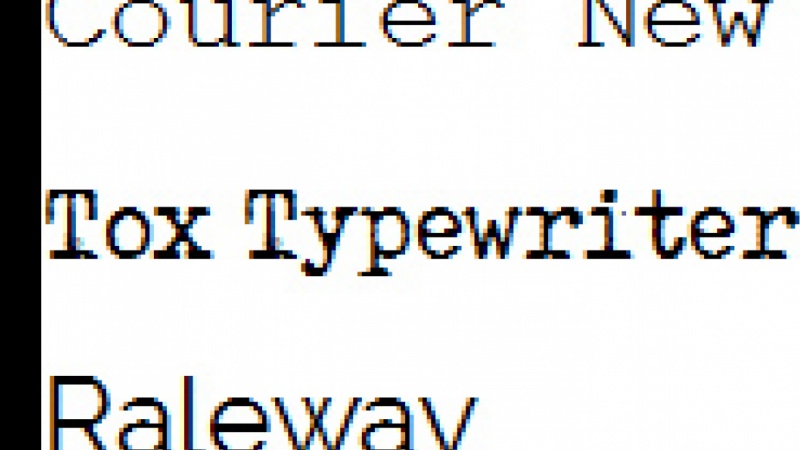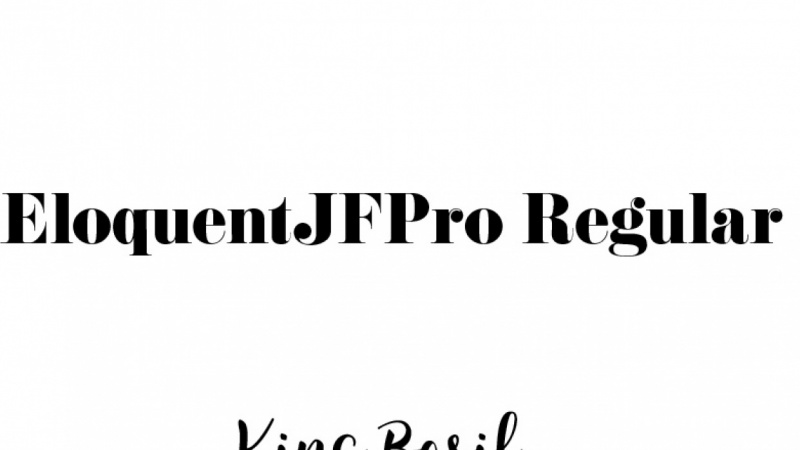
1. Fundamentos de tipografía cómo elegir las mejores fuentes: si alguna vez deambulaste cómo usar la tipografía para que tus proyectos luzcan profesionales donde
querías cómo elegir los mejores fondos? ¿ Encontrarás una gran fuente de respuestas, pues en esta clase aprenderás todos los fundamentos de tipografía necesarios que te harán ir con cualquier tipo de proyecto de diseño que use tipo. Gracias a esta clase, podrás elegir los mejores fondos para tu proyecto, identificar el fondo del que te enamoraste a primera vista y encontrar un montón de buenos fondos tú mismo y decir si vale la pena conseguir. Es una tienda de una sola parada para todos ustedes principiantes que quieran aprender fundamentos de tipografía de una concisa y directa al punto camino adentro, encontrarán respuestas a preguntas como ¿Qué es bueno? topografía fue la diferencia entre una tipografía
2. 1Cómo elegir las mejores fuentes: bienvenido a tomar los fundamentos de Pa Griffey. Cómo Elegir los fondos pasados Ninguna tipografía está contigo dondequiera que vayas al trabajo en la escuela, casa en una tienda por todas partes. Imagínate leyendo un artículo en tu periódico favorito navegando por la Web para conocer lo que es bueno del mundo. O tal vez estás revisando la tarea o el diseño de alguien. Cuál currículum es mejor. Ahí hay tarjetas de visita. Línea en su escritorio, correo de bancos y oficinas o manual para una impresora nueva. Café para ir de su cafetería favorita y estás mirando un cartel colgado en tu pared que dice, Haz más apagado por lo que te hace feliz. Solo quieres echar un vistazo fuera de tu ventana, y no puedes perderte una enorme cartelera invitándote al cine para ver la última película de Woody Allen. Incluso si no eres un escritor profesional o el mismo pensamiento de escribir algo te hace sentir que estás a punto de ser presentado a toda la Inquisición, definitivamente
has escrito algo en el pasado, o al menos reescrito. Podría haber sido un ensayo científico. Reanudar una carta a un cliente o un informe financiero anual. Podrías ser blogger o has diseñado tus propias invitaciones de boda o etiquetas para tarros con especias. O tal vez estás a punto de empezar a diseñar sitios web, logotipos o diversos materiales impresos. Cada vez que pones algún impuesto en el proyecto en un papel o en una pantalla de computadora, haces que la tipografía suceda, hablando
brevemente a tu tipógrafo y este curso trata de que te conviertes en
tipógrafo de bateador .
3. 2Qué es la tipografía: Entonces, empecemos con las tres cosas importantes que debes saber sobre la tipografía. Entonces, en realidad, ¿qué es la tipografía? Si bien la tipografía está diseñando letras, números y signos, es letras, números, signos, palabras, oraciones, párrafos, columnas y blanco espacios de alguna manera, por lo que crean una integridad armoniosa, limpia y atractiva, que está sirviendo al texto y al lector Recuerda respetar a tu lector. La tipografía debe estar sirviendo al lector, no a la oferta. Una famosa Strider ha estado realmente comprometida con escribir su nuevo libro. Un blogger está poniendo otro interés en post sobre su blogueado. Un diseñador está inmerso en crear un nuevo póster. Todos los creadores dedican mucho tiempo a los proyectos para hacerlos tan perfectos como
sólo pueden ser. Pero los lectores no tienen tanto tiempo. Los lectores buscan información. Quieren aprender algo,
revisar algo, obtener una opinión para que naveguen por miles de sitios web y libros. Leerán en Lee aquellos que demostraron valer la pena su tiempo. No leerán un artículo ilegible. No volverán a una página web donde no puedan encontrar nada. Tampoco volverán a un blawg caótico. Es más importante cómo escribes algo, no lo que escribes, al
menos al principio,
Y la tipografía es una herramienta que te ayuda a captar la atención del lector. Una buena topografía hará que el lector note el contenido que es significativo para el otro. Mucho más rápido. No tendrás que perder tiempo para leer todo el texto para decidir qué es importante o qué intentó decir el autor. Aunque el impuesto sea excepcional, Pero fue escrito usando calibri de 10 puntos, el lector se aburrirá con él. Nunca volveré a ello. Una buena topografía ayudará a fortalecer el texto, significado y mantener la atención del lector por más tiempo. A veces extrañamente es mejor que bonito. La tipografía debe ser útil. topografía es una forma fuera del arte aplicado. No tiene sentido diseñar letreros viales usando un fondo funky porque perderán su
propósito principal . En lugar de ser informativos, se
volverán distrayentes. El objetivo de una buena tipografía es aumentar el significado de la información que queremos
transmitir al lector. No importa cuánto lo intentemos, cuánto tiempo los pasemos eligiendo los fondos o configurando el koerting, todo
será para nada si el lector no puede leer mensaje
4. 3Whats la diferencia entre un tipo y una fuente: ¿ Cuál es la diferencia entre un tipo de letra y un fondo? Creo que el mayor error que comete la gente al hablar de tipografía es tratar tipografías y las fuentes como sinónimos. Recuerda, este tipo se enfrenta a una recaudación de fondos relacionados. Se puede pensar en una tipografía como un diseño de una familia de tipos y como cada tipo de familia, las familias tienen nombres y un ejemplo de un nombre de familia tipo es Laura. tipografías son diseños como Laura Monserrat o Poppins, y los diseñadores de tipos crean tipos de letra. Laura es una familia de tipografías. Una tipografía, no un fondo de fondo, es tipo en una tipografía, un miembro de una tipografía, familia o una variante de una tipografía. Entonces volvamos a nuestra tipografía Laura. Ejemplo. Laura Regular, Laura Italic, Laura Bold y Laura Bolt Italics son todos fondos de la tipografía Laura. Un fondo es en realidad cualquier variante en una tipografías espera con estilos y tamaño. Por ejemplo, cursiva de
32 puntos de flora es un fondo, y también lo es 24 Laura Bold. A veces la gente piensa que las fuentes son realmente tipografías digitales, mientras que las tipografías son físicas. El convenio de nomenclatura es el mismo para el tipo digital y físico. Rostros fondos referidos toe esperas con estilos y tamaños y tipografías son algo así como nombres
colectivos off sets off fondos relacionados. En ocasiones, a una tipografía se le conoce como familia de fuentes. Si te gusta un diseño Web, probablemente
te hayas encontrado con familias formadas en lugar de tipos de letra.
5. 4¿Qué es las Typefaces más importantes: hay miles de tipos de letra y fondos diferentes. Es por ello que es difícil llegar a una clasificación que satisfaga a todos . Existen muchas formas diferentes de clasificar tipos de letra, dependiendo del tiempo que se hicieron. Proporciones de estilo técnico, estado de ánimo que crean y demás. Por lo que para los efectos de este curso, vamos a enfocarnos en tres categorías básicas de fondos. Serán útiles para entender cuándo estás después de elegir un fondo adecuado o quieres combinar fondos para tu proyecto de diseño. Empecemos con las tipográficas serif. Se basan en guiones tempranos escritos a mano, manteniendo algunas características fuera de las líneas de pincel y serifis, que son esas pequeñas líneas que salen de los bordes de letras y símbolos. Muchas personas consideradas sirven tipos de letra para ser más fáciles de leer en obras impresas, por lo que con mayor frecuencia se utilizan para la copia corporal en documentos impresos. Hay miles de tipos de letra serif disponibles hoy en día, por ejemplo, estilo
antiguo transitorio, moderno o losa. Algunas de ellas son solo tipográficas viejas traídas al mundo moderno, y digitalizadas y otras se elevan por encima de la multitud y traen algo fresco a este estilo de tipo. Algunos de ellos, caracterizados por la fuerza de letra gorda, fueron diseñados para ser notados. Algunos de ellos han creado contrastes entre trazos gruesos y finos y son más nítidos en su apariencia. Un hijo, tipografía
serif, es una tipografía sin Serifis. El término canciones en francés significa sin, por lo que algunos Saref estarían sin chaleco. El sensor Sheriffs es mejor en tamaños pequeños porque los fondos sobreviven a la reproducción y manchado debido a sus formas simples. En los siglos XIX y XX, hubo realmente una explosión de nuevo sensor de diseños. Son características manuscritas fueron despojadas, lo que nos dio estas tipográficas modernas que conocemos hoy en día. Al principio, estas nuevas cartas fueron calificadas de grotescas, probablemente porque parecían incompletas y tal vez incluso feas. Estos términos todavía se utilizan para describir algunos sirve. hoy. Los hijos de las tipográficas se categorizan aún más como humanista geo métrico y las
tipográficas de script neo grotescas se basan en las formas hechas con un pincel o bolígrafo flexible. A menudo tienen trazos variados y fluidos creados por la escritura a mano. Están organizados en tipos formales altamente regulares similares a la escritura cursiva y guiones más sueltos, más casuales. cuanto a los guiones formales, las letras en su forma original son generadas por una pluma o un trozo metálico de un panel. Ambos son capaces de crear trazos finos y gruesos. Estos tipos de letra se utilizan con frecuencia para invitaciones y diplomas para crear un elevate, una sensación elegante. Los guiones casuales muestran una mano menos formal, más activa. Los trazos pueden estar muy bien con, pero a menudo parecen haber sido creados por un pincel húmedo en lugar de una punta de pluma.
6. 5qué son las variantes más importantes de las Typefaces: ¿ cuáles son las variantes más importantes fuera de los tipos de letra? Para poner las cosas técnicamente pero lo más claramente posible, el peso de un fondo en particular es el grosor de los contornos de los personajes. Relativo a su altura. Una tipografía puede venir en fondos fuera de muchos pesos de punta ultraligera, perno
extra o negro. Son muchos los nombres que se utilizan para describir el peso de un frente, y a ese nombre depende de las ofertas de fondos. Pero su relativo del orden suele fijarse con de una tipografía se determina en relación a su altura. Tipografía. Diseñadores y fabricantes han utilizado tradicionalmente términos para tipos de letra, con principalmente para diferenciar la defensa dentro de una familia de tipos de letra. A pesar de que algunas tipográficas individuales, especialmente estos diseños de visualización, incluyen algunos de estos términos en sus nombres, tipografía con generalmente se clasifica como condensada, normal y expandida con muy niveles fuera condensación y expansión. ¿ Y los estilos telefónicos? A las escaleras orientadas verticalmente se les conoce generalmente como romanas. Esas letras cuidadosamente elaboradas que se asemejan a la escritura a mano y se inclinan, a
veces más y a veces menos pero generalmente a la derecha o general llamada cursiva, y los personajes que han sido redibujados mecánica o digitalmente para inclinarse hacia la derecha son conocido como tipo oblicuo. se utiliza para los mismos fines que el tipo cursiva. No obstante, a diferencia de la cursiva, no usa diferentes formas de glitch. Es el mismo vislumbre que el tipo romano, excepto inclinado. Este enfoque menos elaborado es utilizado por muchos atardecer de tipos de letra. Los pequeños mayúsculas o campamentos pequeños son mayúsculas, o caracteres mayúsculas, establecidos a la misma altura y peso que las letras minúsculas circundantes. Las tapas pequeñas bien diseñadas no son simplemente versión escalada hacia abajo fuera de las tapas normales. Normalmente conservan el mismo peso de trazo que otras letras y tienen un aspecto más amplio. Legibilidad racial cuatro, mínimo
estándar, nuestras cursivas regulares y versiones audaces desde el punto de vista del proceso de diseño, cuantas más versiones sea el bateador, el tipo regular es una versión estándar de un tipo de letra. cursiva se utiliza mejor para enfatizar puntos clave en el interior gravado impreso. Citaciones, cotizaciones en
bloque, abreviaturas fiscales
preliminares o marcando pasajes que tengan un contexto diferente, como palabras de lenguas extranjeras, títulos de
libros, etcétera. Un frente en negrita hace que las letras sean más oscuras que el texto circundante. Con esta técnica, el texto enfatizado destaca fuertemente del resto, lo que debe utilizarse para resaltar ciertas palabras clave que son importantes, por lo que es más fácil escanear visualmente los gravados. Por ejemplo, diccionarios
impresos suelen usar negrita para sus palabras clave
7. Juego de métodos de 6Shape: Tomemos un descanso rápido. ¿ Qué dices? Pasemos al sitio llamado método de punto de forma punto punto a Ver donde vamos a jugar un pequeño juego de modelado de letras. El modo en que juegas aquí es simplemente como tratar de recrear al
diseñador de letras original . Entonces para empezar a ir a hacer es hacer click en este adulto rosado aquí mismo y arrastrar las letras. Por lo que realmente estamos creando y recreando la escalera que comparando o tratando seguir el diseño original. Entonces voy a mover este punto aquí abajo, y como pueden ver, hay 10 diseños y cada uno lo seguirá. Cada diseño siguiente se está volviendo cada vez más difícil, y en realidad se pueden aprender algunas trivialidades sobre estos últimos diseños sobre las tipográficas . Aquí se puede ver el nombre de la tipografia, el diseñador y el año en que se creó. Entonces si solo trato de igualar el diseño original arrastrando estos grandes puntos así tal vez solo un poco, tal vez eso sea un poco más, pero demasiado, tal vez a algún lugar aquí llegué a que no soy el mejor en este juego. De verdad creo que debería ser mejor que yo en esto. Entonces después de que estés contento con tu recreación, solo dale a Comparar para ver lo cerca que estás del diseño original y obtengo el 80% lo cual no es tan malo. Pero cuando vaya a la siguiente letra, las cosas se complicarán aún más. Por lo que definitivamente prueba el método de punto de forma que una letra de forma de C Misha va a dar forma a juego y definitivo. Diviértete con él y te veo de vuelta en la clase.
8. 7por que debes buscar la fuente: cómo identificar una fuente que te guste cuando estás visitando un sitio web, Mirando algunos gráficos en redes sociales o cualquier tipo de material impreso, puedes detectar una tipografía interesante. Necesitas desesperadamente saber su nombre porque quieres usarlo en uno de tus propios proyectos. Bueno, hay algunas formas en que podrías identificar primero un nombre de tipografías. Echemos un vistazo a la fuente en la publicación de hoy. Un teléfono Kala es una breve declaración que contiene información sobre la publicación de un libro como el Lugar de publicación, el Editor y la fecha de publicación. También puede contener el nombre del software utilizado para ensamblar los nombres de texto de los fondos utilizados, pero también los nombres de las personas que inspiraron o ayudan al autor. Y si te interesa el desarrollo de diseñadores web, puedes usar las extensiones de navegador incorporadas como firebug en Firefox o Inspector en Chrome para obtener la información sobre la fuente utilizada, y la propiedad que quieres buscar se llama encontrado Familia
9. 8 5 Herramientas estupendas para identificar una fuente: Aquí te presentamos cinco grandes herramientas que te ayudarán a identificarte han encontrado, si puedes encontrar la fuente. Por suerte, puedes usar una sobre las herramientas de salvamento que puedas. Por ejemplo, prueba extensiones de navegador como la cara de fuente Linda. Este es un plugging disponible para Firefox, chrome y safari. Simplemente puedes encontrar Google Face Ninja chrome o un fondo cara Peligro Firefox. Después ve al sitio web de extensiones e instala la extensión. Ahora todo lo que tienes que hacer es hacer clic en los enchufes. Yo vengo y luego solo pasas el rato sobre un determinado pedazo de impuesto para obtener la información sobre el
fondo en particular . Basta con hacer click en ataques para ver una ventana emergente donde impugnas el fondo en un texto de tu elección. También puedes probar el modo de enmascaramiento, que deshabilita todos los gráficos del lado s, por lo que es más fácil para ti enfocarte solo en el texto. Otra herramienta útil de identificación encontrada se llama encontrada. Todo lo que necesitas hacer es remolcar terminar este fondo a tu barra de marcadores, y vas a dejar que comience el proceso de identificación Al mirar teléfonos en un
sitio web determinado , haz clic en el marcador para activar el proceso de identificación y haz clic en un pedazo de texto. Obtendrás una respuesta inmediata con el nombre de la tipografía, el tamaño y el estilo. Desafortunadamente, a veces una tipografía que nos gusta no se guarda como fondo Web. Entonces, ¿y si solo tenemos una imagen con interés en impuestos o solo tenemos algún
material impreso ? Bueno, hay algunas soluciones a este problema también. El primer policía llamó al aireador del partido telefónico, y el peso peor es realmente sencillo. Todo lo que necesitas hacer es remolcar, subir una imagen con algún texto o seguir que tomaste, por ejemplo, una foto de un libro. Eventualmente, el programa te mostrará una lista de fondos que pueden coincidir con tu impuesto, e incluso si no lo consigue exactamente bien, te dará algunas buenas alternativas. El de al lado se llama What The Front y yo creo que es el
dedo de identificación telefónica más antiguo en es amable. Funciona casi igual que un estofado encontrado traidor de partido. Es decir, sólo sube la imagen, dale a la herramienta algunas pistas en cuanto a las letras en la imagen, y como resultado, obtenemos unas sugerencias mejores o peores. Ahora, ¿qué fondo es una identificación de fuente más grande? ¿ Servicio en línea? Podemos subir una imagen igual que en el mundo la fuente. También podemos proporcionar un tu l de cierta imagen. Podemos añadir una extensión de navegador. O podría utilizar el foro para preguntar a esos expertos en tipografía. Pero recuerda, los diferentes servicios tienen bibliotecas de fuentes un poco diferentes. Si una de las herramientas no produjo resultados satisfactorios, solo
vale la pena probar las otras.
10. 9Cómo identificar una fuente propia: Si quieres jugar a un detective de tipografía real o crees que será un gran juego de fiesta, puedes dejar que tu te ayudo en identificar fondos para que puedas iniciar el proceso de eliminación. Entonces empieza con una amplia clasificaciones en ¿Es el frente Saref san serif o guión? O tal vez se ve tradicional moderno, o parece una Slap Saref. Entonces las formas de letra son extendidas geo métrica o convencidas ¿Cuál es el peso? Y en este punto, lo habrás reducido drásticamente, y podrás empezar a buscar características distintas. Por ejemplo, vals la altura X relativa. ¿ Dónde se llenan las barras transversales? ¿ Qué tan grandes son las aperturas y botellas son inusuales las del remitente A o de los inconformes? ¿ De qué forma son los títulos y periodos? Identificar teléfonos se vuelve más fácil a medida que aprendes más sobre ellos. Cada teléfono tiene algunos personajes con los detalles inusuales. Si notas y recuerdas, esos detalles podrán identificar más fondos
11. Juego de 10Typeterms final final2: Tomemos un descanso rápido, ¿sí? Echemos un vistazo a la terminología de tipo. No aprender apenas poco sobre la terminología ayudará. Tienes una mayor apreciación por tipo. También te ayudará a identificar diferentes tipos de letra y fondos. Y eso, a su vez, te
ayudará a tomar mejores decisiones sobre las fuentes que usas. Entonces, ¿qué hay de cabeza en el www dot supremo, ese sitio web de términos de TV aquí. Podrás aprender todo sobre la terminología de tipo solo para dar click en una parte que te
interesa , y obtendrás algo más de información sobre ese elemento en particular. Por lo que definitivamente Jack este sitio web fuera. Familiarízate con la terminología tipo y te veré de vuelta en clase.
12. 11por que las fuentes son como la ropa: tres cosas que debes saber antes de elegir un fondo. Entonces, ¿por qué los fondos son como la ropa? No. Elegir el frente es como elegir ropa para un disfraz de duelo de Dennis o un esmoquin. Y te das cuenta de alguna ropa deportiva. Si quieres ir al gimnasio,
la primera impresión que obtenemos de las personas, lugares o cosas es extremadamente importante. Tenemos una tendencia a construir nuestra opinión sobre algo o alguien. A juzgar por los primeros clanes, se aplica no sólo a las personas sino también a los libros, periódicos, carteles o sitios web. Es necesario pensar si todos los elementos y eso incluye los fondos fueron elegidos correctamente en términos de las metas del proyecto. Tu elección funk debe fortalecer la idea del proyecto y ayudar al lector a obtener la idea. Ten cuidado de no dejar que tu propio gusto te guíe demasiado. Es fácil dejarse tentado por teléfono que amas y que es hermoso en sí mismo pero no lleva el mensaje correcto y puede destruir todo el proyecto. Entonces no te pongas vestido de noche Cuando vayas a un gimnasio, gente pensará que estás loca. Si no eliges el fondo adecuado, distraerás a tu lector de las metas del proyecto
13. 12Typefaces tienen sus propios lugares: las tipografías tienen sus propios lugares, y uno de los errores más comunes que cometen los principiantes es no darse cuenta para qué son
las diversas categorías de fondos más adecuadas. Por ejemplo, tipografías de
cuerpo versus estas tipografías de placa. Nadie. tipografías están usando copia corporal como libros, revistas, periódicos o sitios web. Estos fondos son fáciles a los ojos y fáciles de leer. Es importante que no estén distrayendo, por lo que los usuarios pueden pasar fácilmente por el tipo expositor gravado o decorativo. rostros, Losrostros,
por otro lado, no
son adecuados para una larga lectura de estas acciones. Estos son el tipo de padre quiere brillar en la alfombra roja más que la
propia Kim Kardashian . Vienen en diversos grados fuera de utilidad de los audaz all caps teléfonos que podrían ser utilizados para titulares a los teléfonos que son muy obvios. Tales letras nevadas que aman saltar en las tarjetas navideñas. Este tipo de teléfonos pueden ser divertidos y tener sus usos. Pero el buen diseño, especialmente el diseño destinado a los negocios, a menudo tiene más saciedad que eso. Los fondos de pantalla pueden tener un gran impacto cuando se usan de la manera correcta, pero cuando se usan incorrectamente, pueden hacer que un diseño parezca ocupado y aficionado. En pantalla corta, tipografia es diferente de las caras tipo cuerpo y que no son, también, que no son fáciles de leer en longitud y deben usarse con cuidado y con propósito.
14. 13y hay fuentes que se combinan todo todo: por lo que ningún evento ni las reformas que coincidan con todo. Si alguna vez estuviste atascado en un proyecto porque no pudiste encontrar el fondo adecuado o encontraste demasiadas formas que tú que sentías que eran geniales, puedes recurrir a tipografías de caballo de batalla es esas tipografías que son universales, neutras y se verán bien en la mayoría de los proyectos. Son a la vez elásticos y discretos, por lo que se ajustarán a la mayoría de los escenarios. Por lo general son las tipografías serif básicas y sans serif las que tienen unos pesos con y estilos diferentes del mismo tipo. Cara podría usarse para diferentes propósitos y elegir una tipografía, pero diferentes estilos te permitirán crear diseños cohesivos y atractivos. Entonces echemos un vistazo a algunos ejemplos de caras de este tipo. Hay fondos de siembra disponibles que son gratuitos de descargar o comúnmente disponibles en muchos sistemas operativos que harán muy bien para proyectos de diseño cotidianos. En la categoría serif. Prueba Georgia y Data Crimson Taxed Droid, Serif o Merryweather. Si buscas sentido, vistazo a la fuente Franklin Gothic Roboto Lotto desde Pro o Merryweather Sam's. Entonces si tu cabeza se está calentando demasiado al mirar las tipografías que crees que se verán muy bien en tu proyecto. Y, como siempre, estás en un horario apretado. Es una buena idea tomó para tipografías universales que te sacarán de muchos
problemas de tipografía .
15. 14BONUS dónde encontrar buenas fuentes: donde encontrar buenos fondos. Si tienes un presupuesto ajustado o solo buscas experimentar en un proyecto más pequeño, hay un montón de buenos fondos llorados disponibles sin costo si solo sabes dónde buscar. El fondo ardilla es probablemente la mejor fuente de fondos. Hay tanto gratuitas como con licencia para uso comercial. Aquí encontrarás una gran selección de fondos escogidos a mano, de
alta calidad que se pueden buscar por clasificaciones, como un sensor serif para script o por etiqueta. Tal horario. Los teléfonos Google retro o angustiados fueron creados principalmente como un repositorio de fondos gratuitos para proyectos de diseño
Web y desarrollo Web. Aquí encontrarás cientos de fondos que son todos de código abierto, lo que significa que se pueden compartir, modificar, personalizar, etcétera y, bueno, están optimizados para la Web. También se pueden descargar para que puedas utilizarlos en proyectos de impresión. Ten en cuenta, sin embargo, que los fondos gratuitos son mucho más propensos a causarte un dolor de cabeza en el futuro. No me perdí. A los personajes les falta soporte de idioma, espaciado
deficiente o un rendimiento de pantalla deficiente. Entonces si hablas en serio con tu tipografía, tu mejor pero más caro pero es invertir en unos fondos pagados de alta calidad. Hay muchos servicios en línea que ofrecen fondos. Puedes comprarlos directamente a diseñadores o fundiciones, o puedes comprarlos en tiendas online. Entonces, por ejemplo, que
puedas comprarlos en mis fondos. Ese kit tipo tranquilo encontró tienda dot com y otros. También puedes echar un vistazo a Creative Market que vienen donde puedes encontrar algunas grandes ofertas en teléfonos y otros materiales de diseño gráfico.
16. Vamos a Sum lo que hemos aprendido: para terminar las cosas, Vamos a resumir brevemente lo que hemos aprendido en el curso. Elegir el tipo de cara correcta tiene un significado enorme para todo tipo de proyectos, desde los que valen millones hasta los que usamos en Lee día a día. Es importante entender que no estamos diseñados para nosotros mismos, sino para los lectores, significa
que los proyectos deben ser legibles y utilizables. Míralo desde tu propia perspectiva. También eres lector,
y sabes lo que te irrita y te desalienta de leer. Hablamos de la diferencia entre el tipo de cara y un fondo. Ahora ya sabes que una tipografía es un grupo de fondos relacionados que forman una sola familia. Por ejemplo, Laura y un fondo es un miembro de una familia, por ejemplo, 12 puntos Laura Italic. También hablamos de los tipos básicos de tipografías como Sarah de San Serif y script . Aprendimos sobre sus variantes y estilos. Las tipografías tienen un montón de pesos que van desde la línea del cabello demasiado pesado y un montón de withs desde condensado para expandirlo. Estilos nos permiten dar un significado especial a ciertos fragmentos de impuesto usarán la
versión negrita de una fuente. Cuando queremos enfatizar las palabras, queremos que el lector preste especial atención y usará cursiva para citar las palabras de alguien
dedo del pie. Identificar fondos que para ganar nuestros corazones miramos herramientas que nos ayudan en el proceso de identificación, como un fan face ninja o lo que El fondo. Recuerda que hay muchas aplicaciones diferentes que ayudan a identificar tipos de letra, así que definitivamente explora otras opciones y para, ya
sabes, encontrar la que crees que sea mejor para ti. También aprendimos a que las tipografías la mitad hay cierto lugar en los proyectos. No se deben usar las tipografías de visualización para crear copia corporal porque su característica no es adecuada para unas largas sesiones de lectura. Son geniales para titulares, sin embargo. Sabemos que hay fondos universales que coinciden con casi cualquier tipo de escenario de diseño, por lo que pueden ser de gran ayuda cuando estás en un horario apretado. Y por último, miramos lugares donde podemos encontrar grandes fondos. Creo que hace falta decir que las fuentes de fondos de Paige como mis fondos tienen
repositorios de reacher , pero puedes encontrar interés en los fondos. Inferiors Resource es como las fuentes de Google también. Esperamos que este curso te resulte útil y que tengas más conocimiento